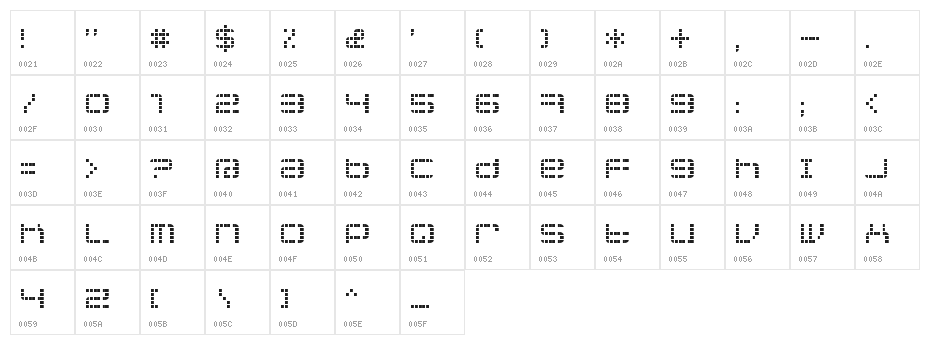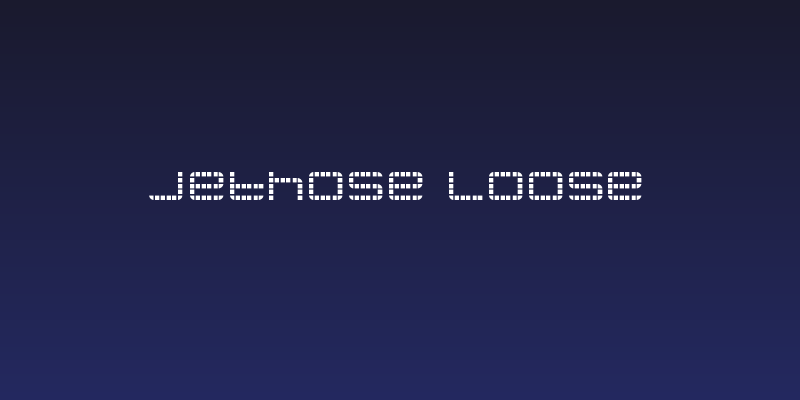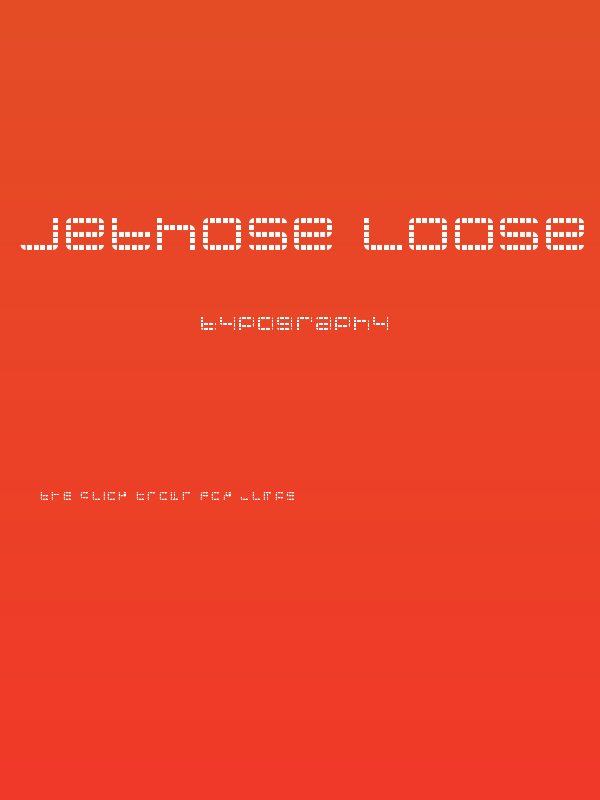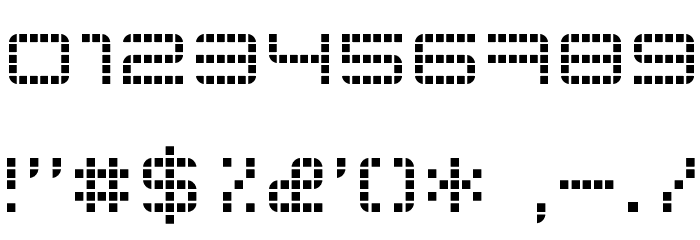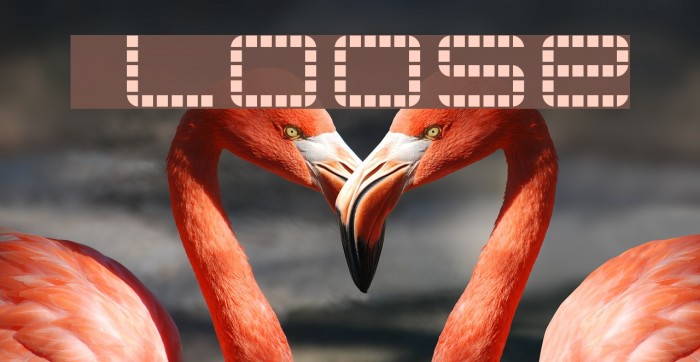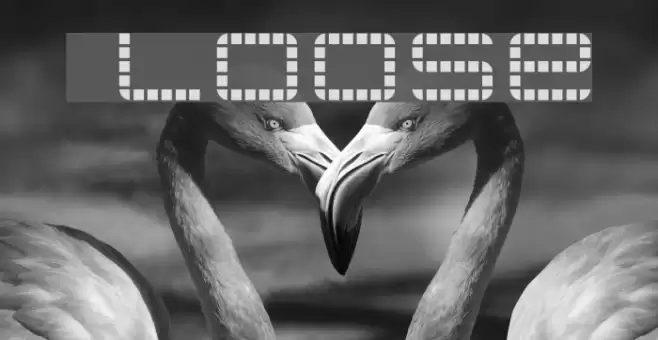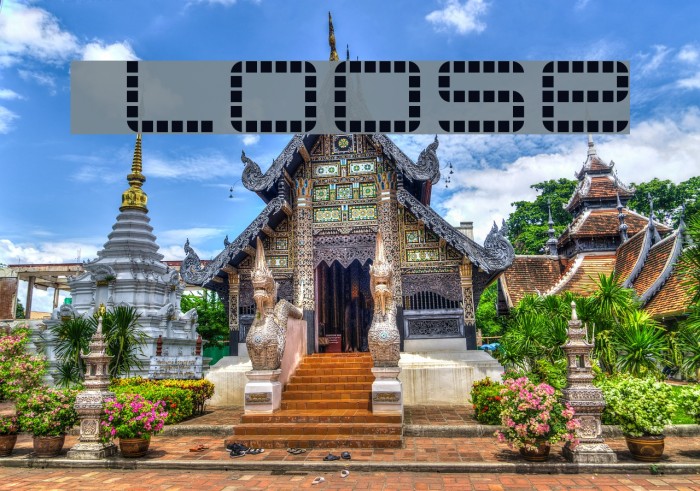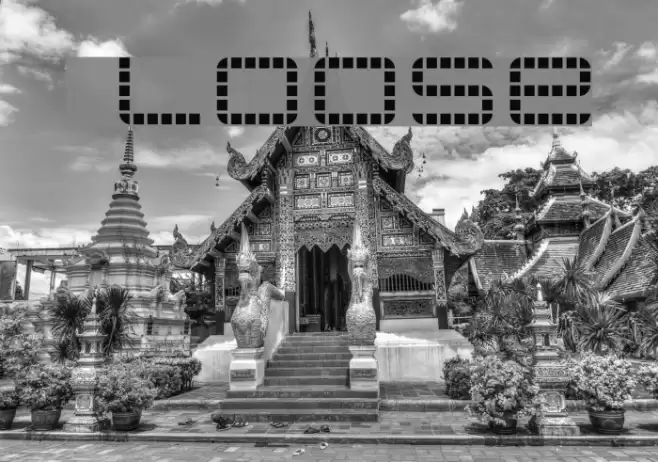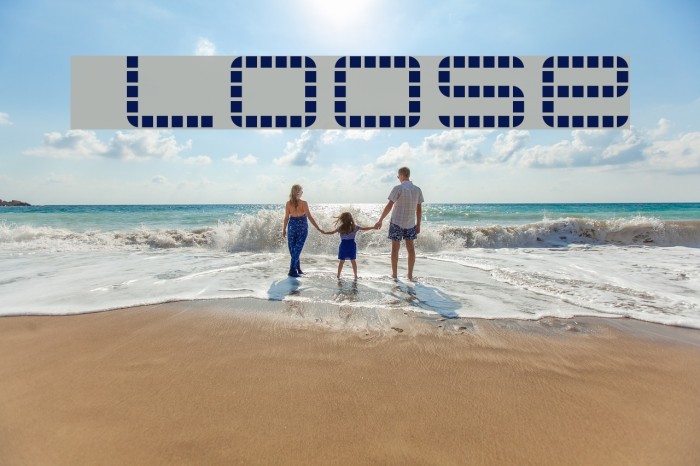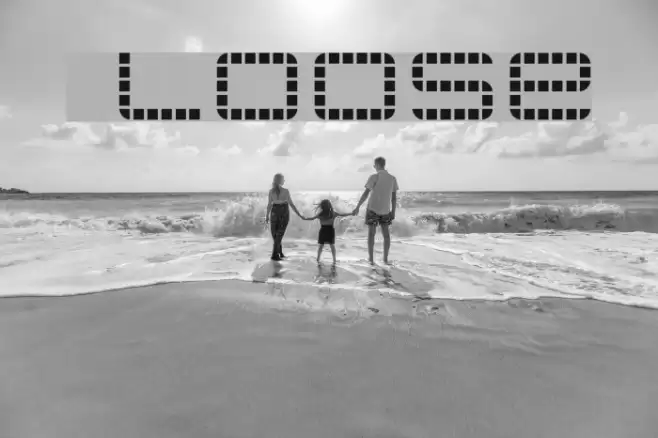
jethose LOOSE Font
✎ Pixel
| Anwendungsfall | Headlines, Logos, Digital displays |
| Vorgeschlagene Projekte | Ideal for digital displays, tech-themed designs, video game interfaces, and futuristic branding. |